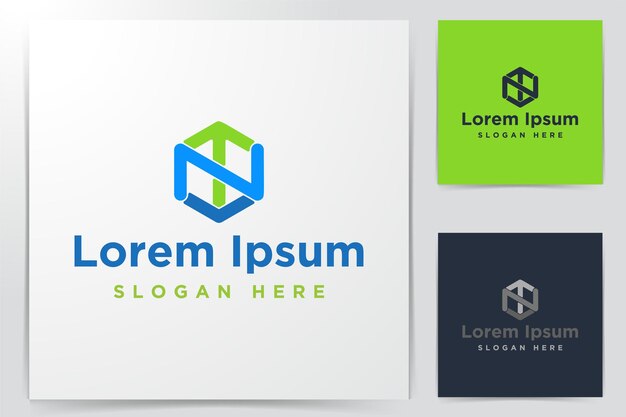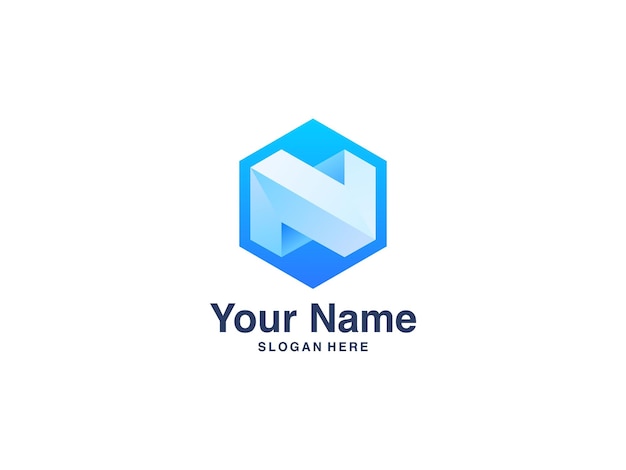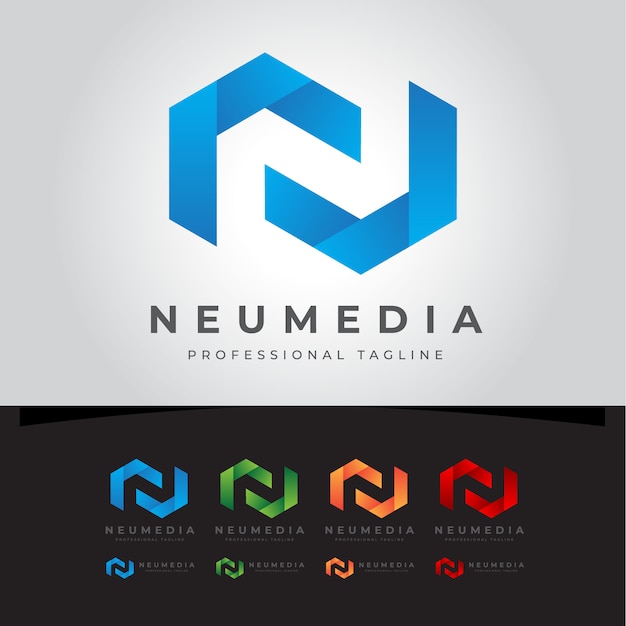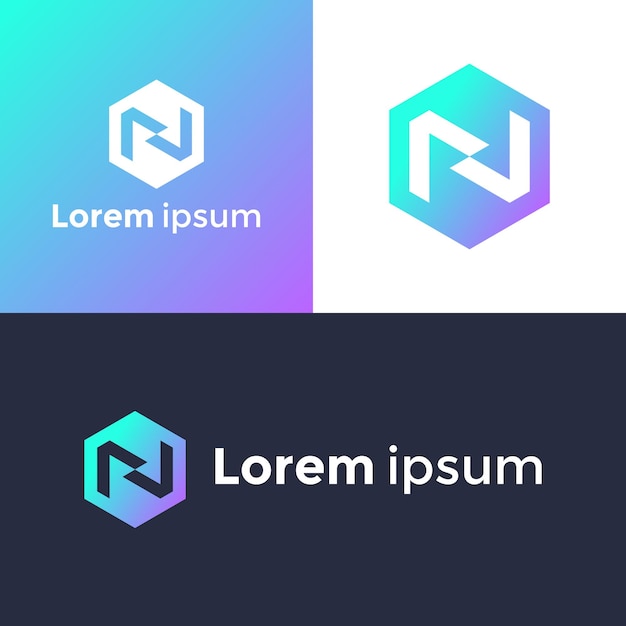
minimalne logo alfabetu litery N proste elementy szablonu czcionki ikona projektu o kształcie wielokąta
Minimalne logo alfabetu litery N proste elementy szablonu czcionki ikona projektu o kształcie wielokąta